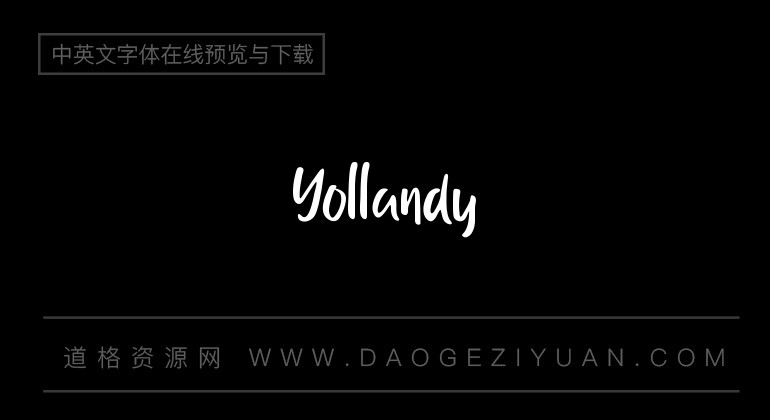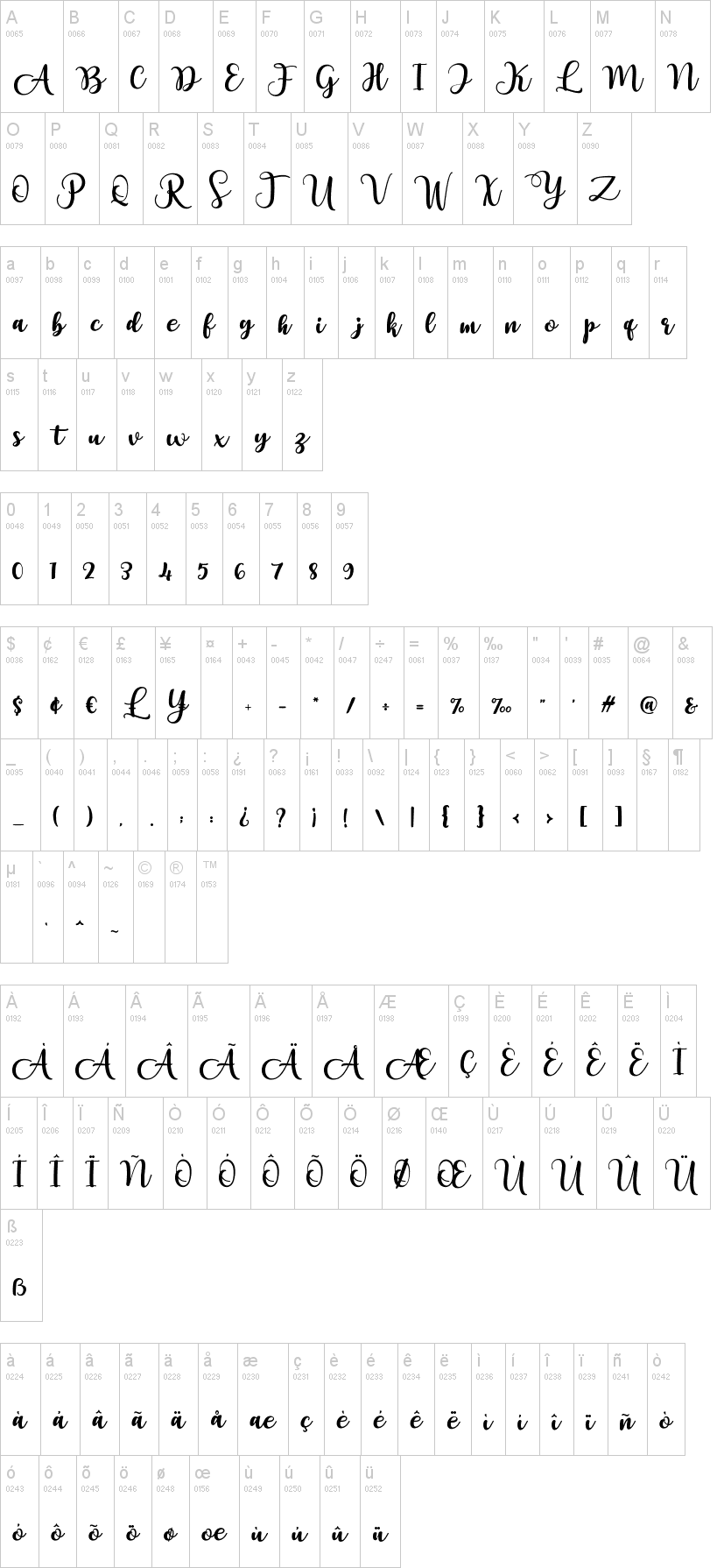
Yollandy
Yollandy 字体是一款简洁明快的平面设计字体,它具有现代、清新、活泼的风格,适用于各种设计项目,如海报、徽标、包装等。Yollandy 字体的字符结构简单明了,适合长文本,具有良好的可读性。另外,它的符号集也很丰富,可以满足您的各种设计需求。
Yollandy是一款非常不错的手写艺术字体,具有很好的视觉感,适合于文化类的宣传设计、商业类品牌的广告和产品包装设计以及个性化文字排版等较多场景。
Yollandy字符映射图